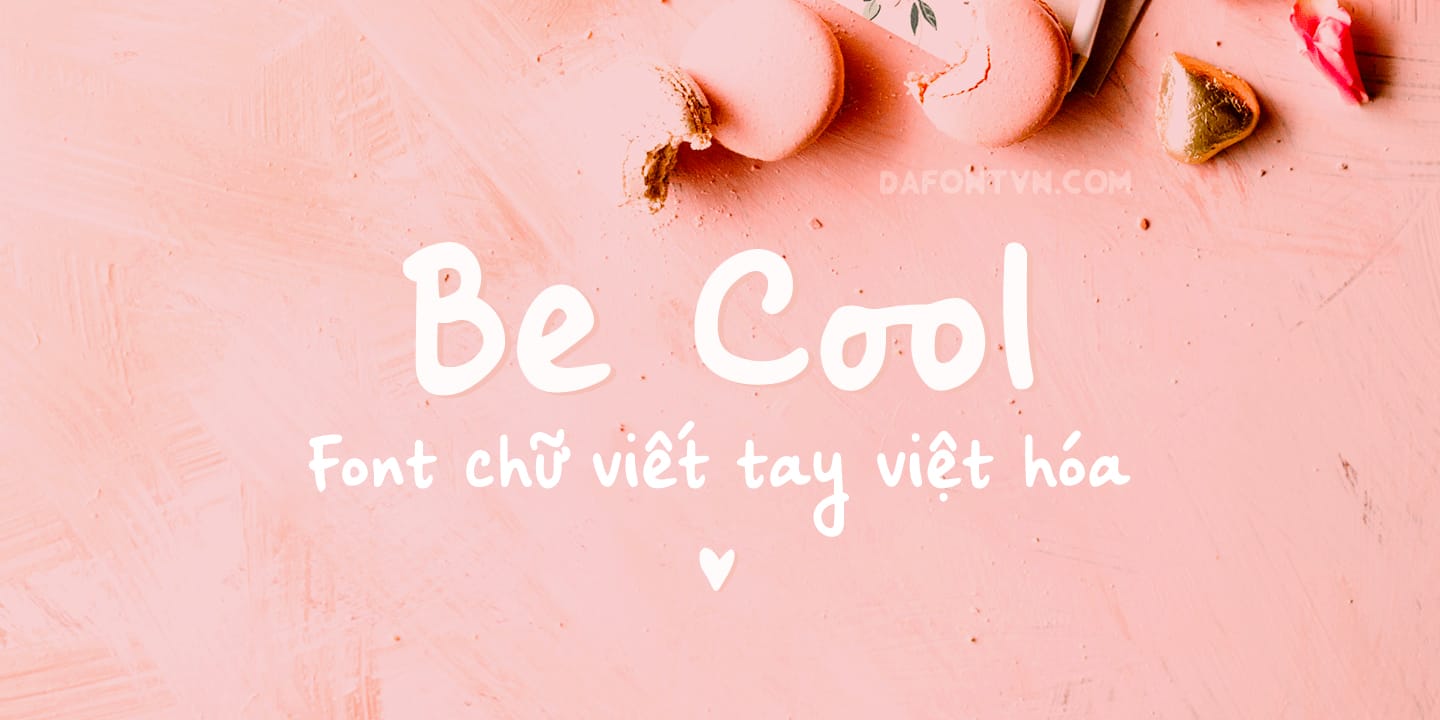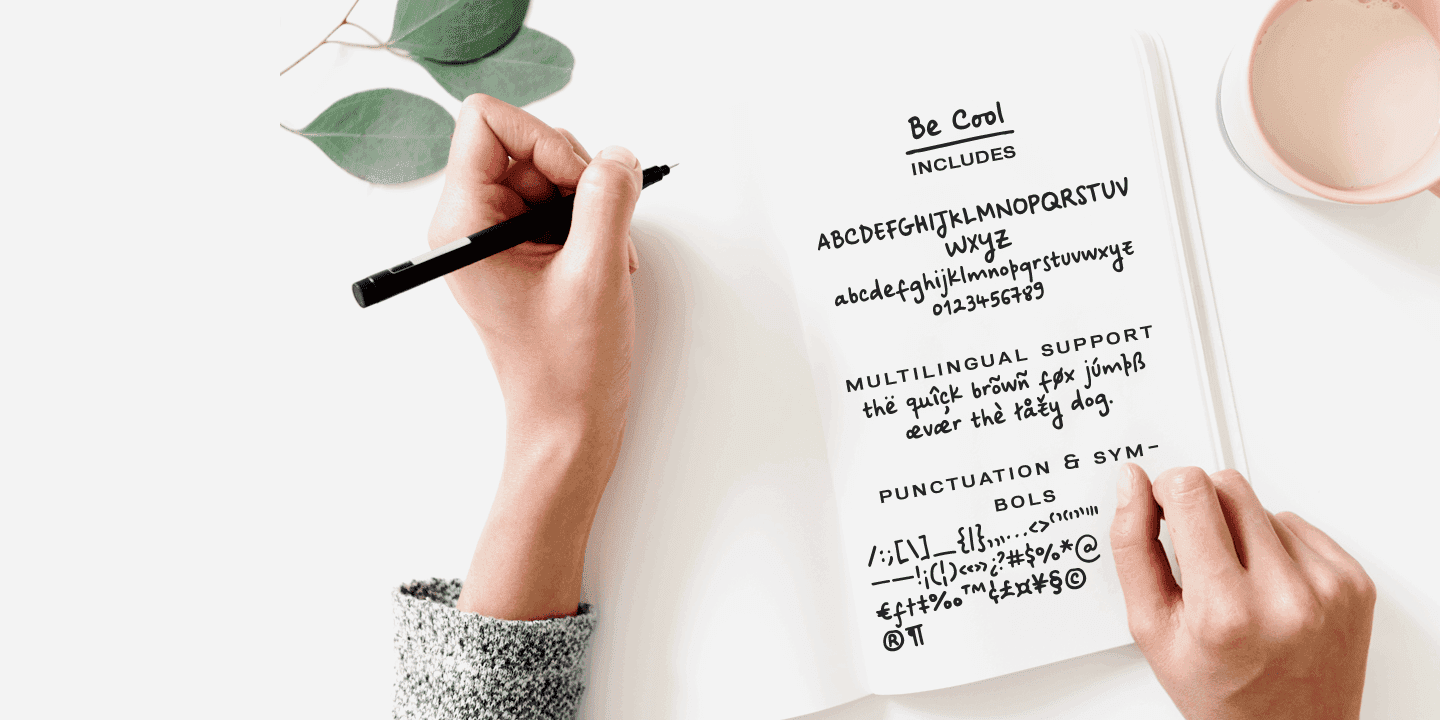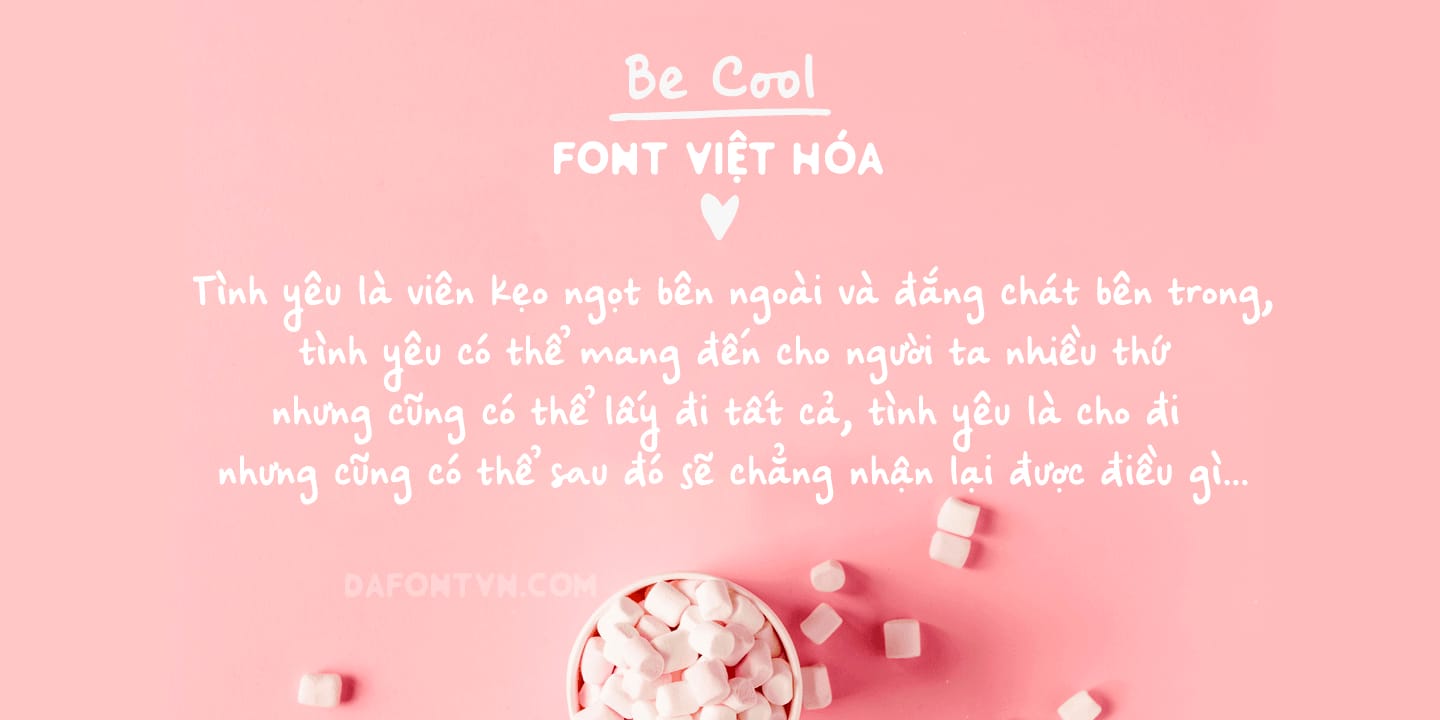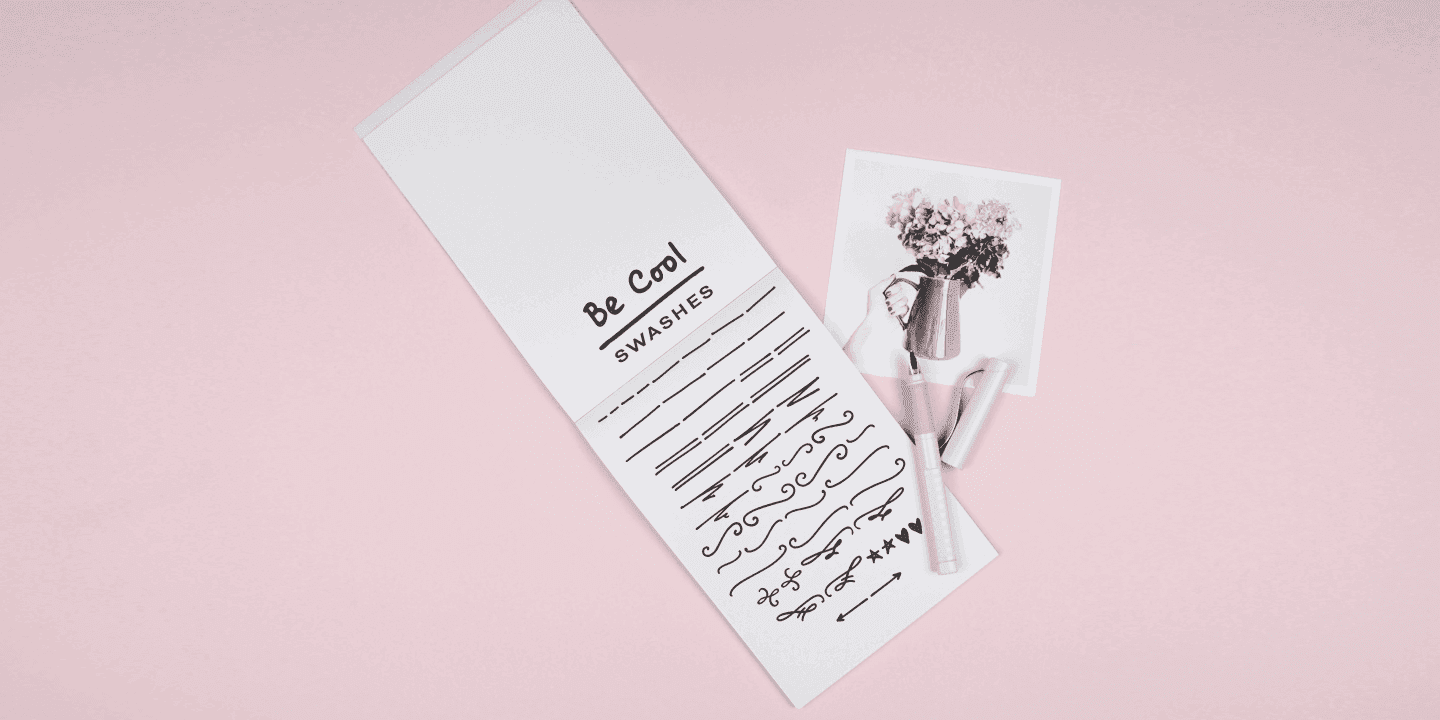
Be Cool là một font chữ viết tay dễ thương với bộ ký tự thay thế (AZ, az) và một bộ bổ sung các dấu nháy và đồ trang trí để giúp trang trí văn bản của bạn.
Font chữ iCiel Be Cool Việt hóa này bao gồm:
– AZ, az, số và dấu chấm câu
– Hỗ trợ đa ngôn ngữ
– Hàng chục chữ ghép mang lại cảm giác viết tay chân thực
Sử dụng Be Cool trong bất kỳ thiết kế nào cần cảm giác viết tay, chẳng hạn như chữ ký, ghi chú và trích dẫn, biểu trưng và thương hiệu.